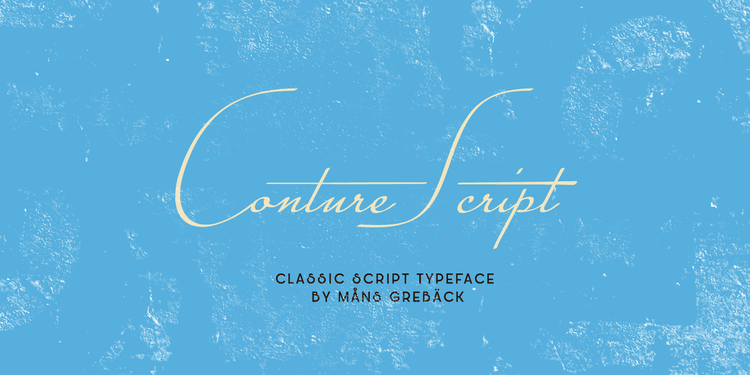
A Conture é uma nova adição no vasto universo das fuentes de script. Introduzida por Måns Grebäck durante 2017, esta fonte tem um charme clássico com contorno fino. Conforme menciona a descrição original, ela foi criada para oferecer uma ampla gama linguística que suporta mais de cem mil caracteres ou “glyphs”. A qualidade do tipo é notável em sua definição meticulosa e detalhada. Uma fonte ideal para qualquer projeto que busque um toque sofisticado, seja para criar a identidade visual de uma marca ou decorar seu site pessoal. Essa fórmula perfeita está especialmente projetada para atender às necessidades dos convites de casamento e blogs, oferecendo uma solução versátil para estilos delicados e elegantes.